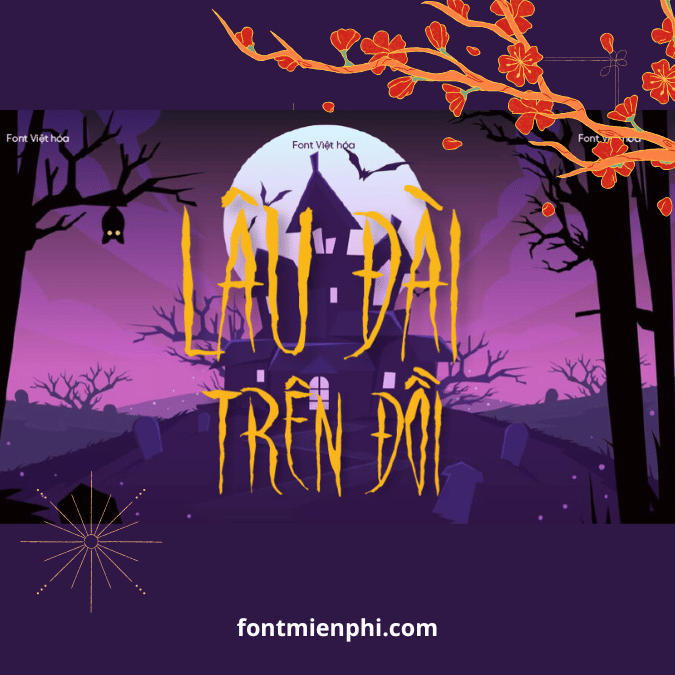
Font Việt Hóa 1FTV VIP Raven Song – Phông Chữ Halloween Huyền Bí Và Ma Mị
1FTV VIP Raven Song là font chữ Việt hóa cao cấp với phong cách Halloween huyền ảo, lấy cảm hứng từ những chú quạ đêm và bầu không khí bí ẩn. Với những nét chữ uốn lượn như lời thì thầm trong đêm kết hợp hiệu ứng bóng ma, font chữ này mang đến vẻ đẹp kỳ bí và sang trọng cho mọi thiết kế.
Đặc Điểm Nổi Bật:
✔ Hỗ trợ đầy đủ tiếng Việt chuẩn Unicode – phù hợp mọi nhu cầu thiết kế
✔ Phong cách Gothic tinh tế – nét chữ thanh thoát như lông vũ kết hợp hiệu ứng bóng đổ ma quái
✔ Chất lượng premium độc quyền – sắc nét trên mọi nền tảng thiết kế
Ứng Dụng Hoàn Hảo:
• Thiết kế poster Halloween cao cấp
• Bìa sách/truyện kinh dị, Gothic
• Nhãn hiệu mỹ phẩm Halloween Limited Edition
• Thiệp mời tiệc ma sang trọng